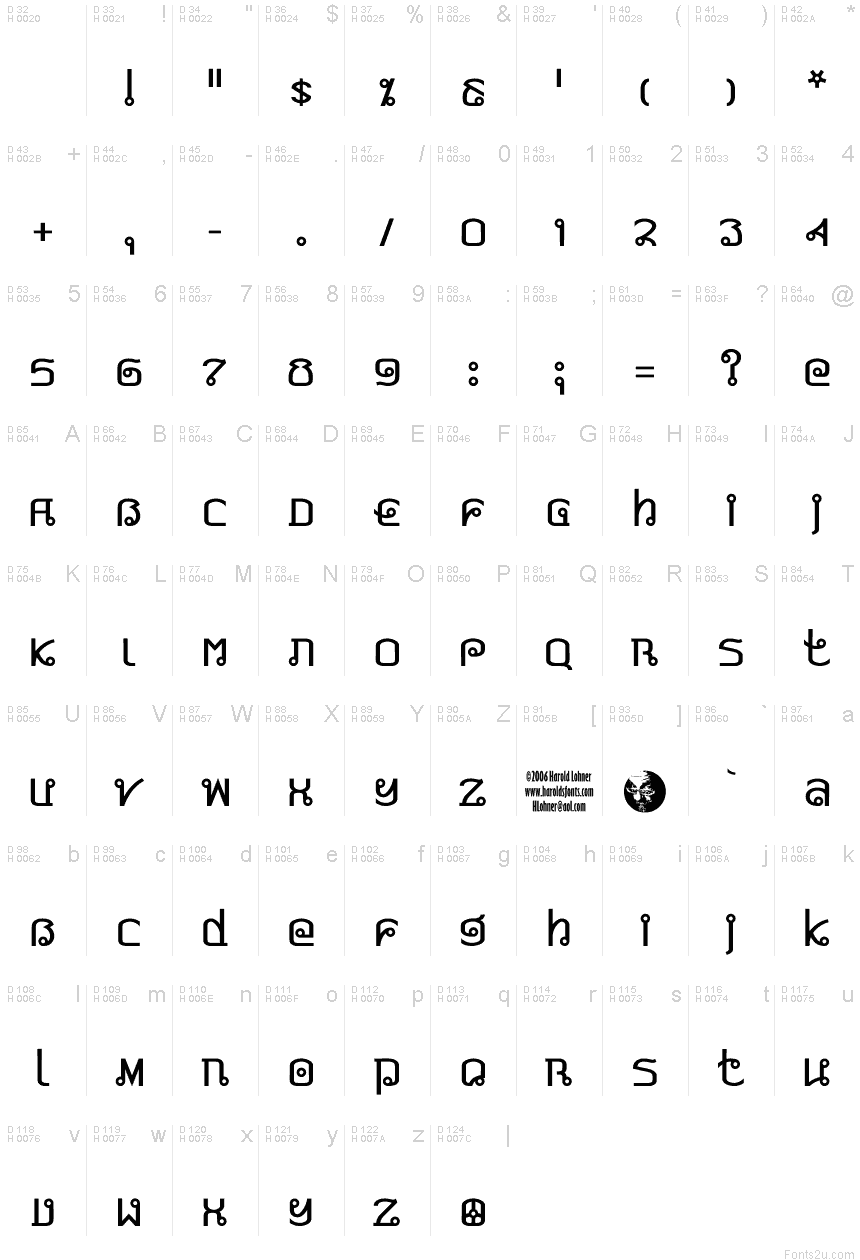
Pad Thai
Pad Thai di Harold Lohner è un font display gratuito di ispirazione thailandese, caratterizzato da tratti fluidi e curve interne che richiamano più il lettering ornamentale che un carattere da corpo del testo. Le forme rimangono aperte e rotonde, con alcuni tratti che si allungano verticalmente per conferire al design un aspetto dinamico e slanciato.
Pad Thai è ideale per l'identità visiva di ristoranti, menu, packaging, titoli di locandine ed eventi culturali, poiché le sue lettere trasmettono un chiaro richiamo alla cultura thailandese senza sacrificare la leggibilità. Questo font gratuito è perfetto anche per loghi e titoli brevi che richiedono carattere in spazi ridotti, specialmente se abbinato a un font più semplice.